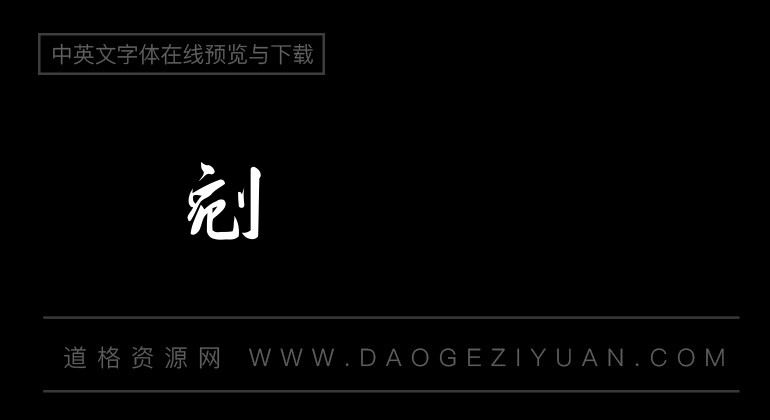
金梅毛匾行
金梅毛匾行字体是一种传统的汉字字体,它的特点是较大的笔画宽度,古朴的风格,以及笔画和空格的精细细节。它通常用于拓印古典文物和古代文献,也可以用于现代文字的排版。金梅毛匾行字体的特点是笔画宽度较宽,细节刻画精细,空格精准,笔画粗细统一,字体稳定,视觉效果优良。
金梅毛匾行是一款非常不错的手写艺术字体,具有很好的视觉感,适合于文化类的宣传设计、商业类品牌的广告和产品包装设计以及个性化文字排版等较多场景。